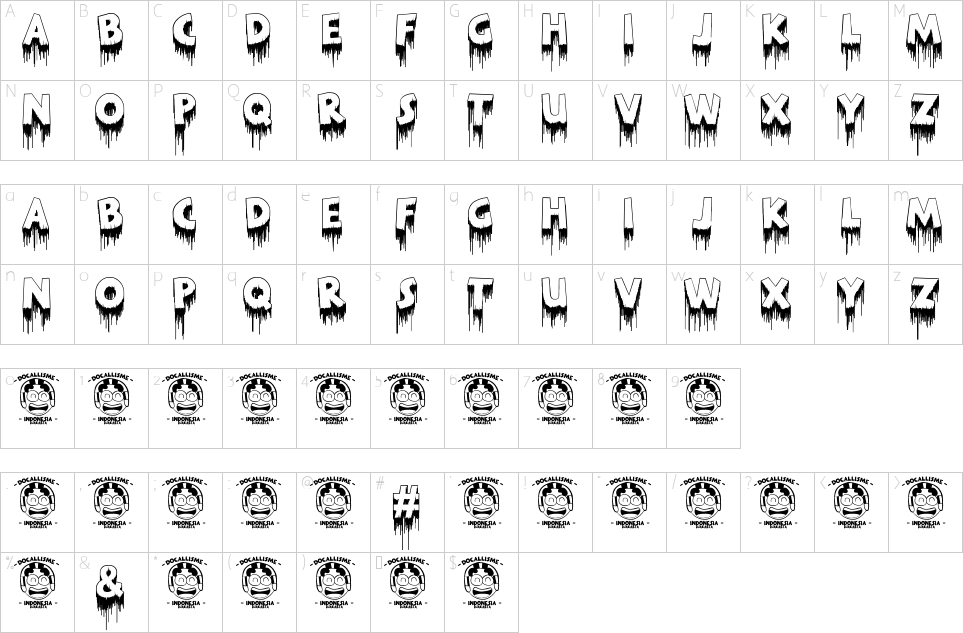
A fonte Merdeka é uma opção gratuita e elegante para designers de todo o Brasil, disponível tanto para Windows quanto para Mac. Feita por Docallisme HAS – Ryal, essa fonte ganhou notoriedade entre a comunidade de designers graças ao seu design atraente e versátil. Com seus 6.696 downloads registrados, Merdeka já prova ser uma opção de qualidade para projetos variados. Se você busca uma fonte moderna e sofisticada para seu próximo trabalho, Merdeka pode ser uma excelente opção, garantindo uma experiência de design harmônica e prática. Descubra por si mesmo o poder desta fonte única e gratuita.